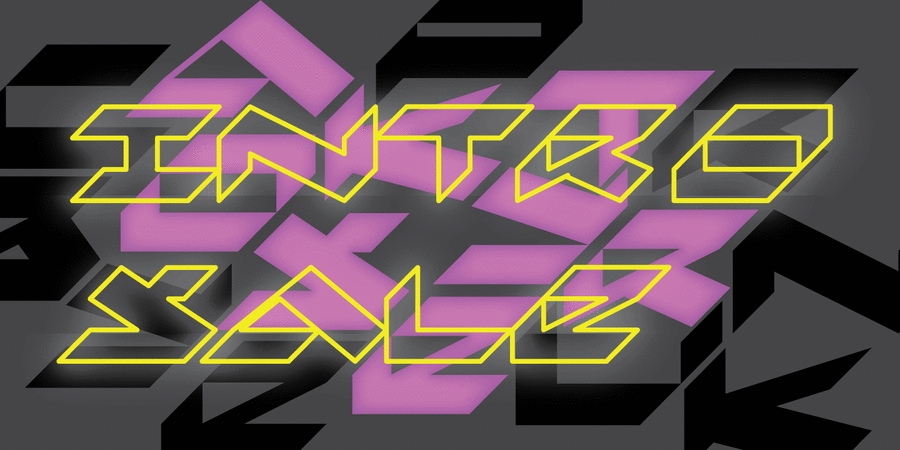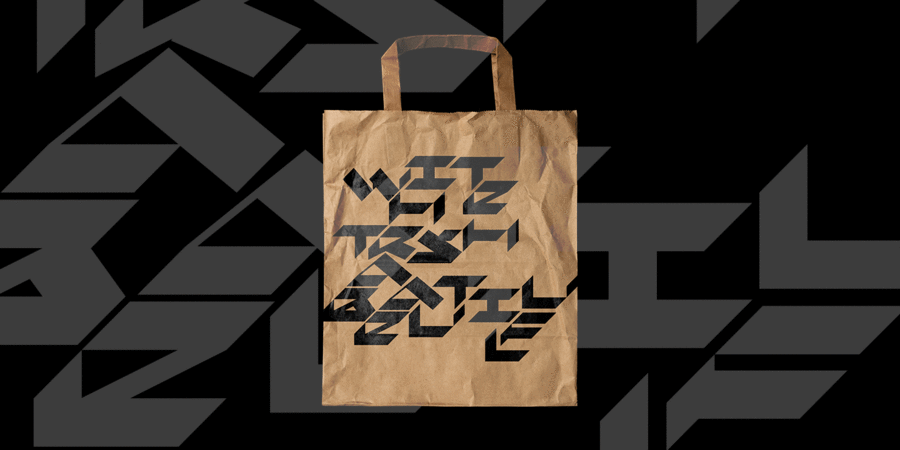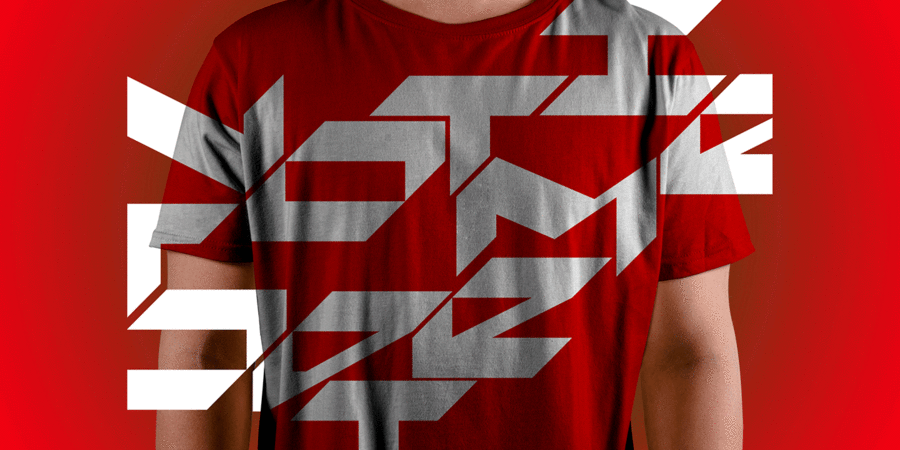
Шрифтова пара з KomSans Regular (1 з 12)Опис шрифта AkoysterВ основі шрифту Akoyster лежить каліграфія широким пером з фіксованим нахилом 45 градусів, практично максимальним для європейської каліграфії. Плюс повна відсутність обертання пера й обмежений кегельний майданчик знаків. У підсумку виходить різка графіка з насиченими знаками. Базовий трекінг налаштований зі значною розрядкою, але, як видно на ілюстраціях, шрифт відмінно працює з абсолютно різною розрядкою. Akoyster вирішений у форматі Unicase, але все-таки деякі відмінності між великими та рядковими є: так Ii у верхньому й нижньому регістрі зберігають відмінність: відсутність і наявність крапки. У комплекті: латинка, акцентована латинка, кирилиця для білоруської, української, російської мов, дві версії Дд і Лл, все знаки пунктуації, набір цифр, спеціальних символи. Шрифт розробив Олексій Коваль у 2020 році.
Асоціації з сімейством шрифтів AkoysterОсобистість і характер гарнітури:
екстремальний, швидкий, рішучий, енергійний, космічний, швидкісний, комп'ютерний, молодіжний, електронний, динамічний, рухливий, оригінальний, тусовочний, клубний, двіжняковий, експериментальний, футуристичний, психоделічний, кислотний, хуліганський, сміливий, ризикований, вуличний, епатажний, ламаний, урбаністичний, зухвалий, небезпечний, гострий, різкий, колючий, грубий, міський, радикальний, нахабний, нічний, запальний
комп'ютер, робот, фантастика, автомобіль, гаджет, девайс, авіація, літак, блокбастер, бойовик, екшен, айтішник, IT, програмування, айті, технології, андроїд, залізо, супергерой, кіберспорт, комп'ютерна гра, екстрим, електроніка, розваги, нічний клуб, вечірка, тусовка, шоу, танець, каскадер, графіті, концерт, ніж, анімація, хакер, Місто, графіка, ілюстрація, шолом Гарнітура асоціюється з віком: